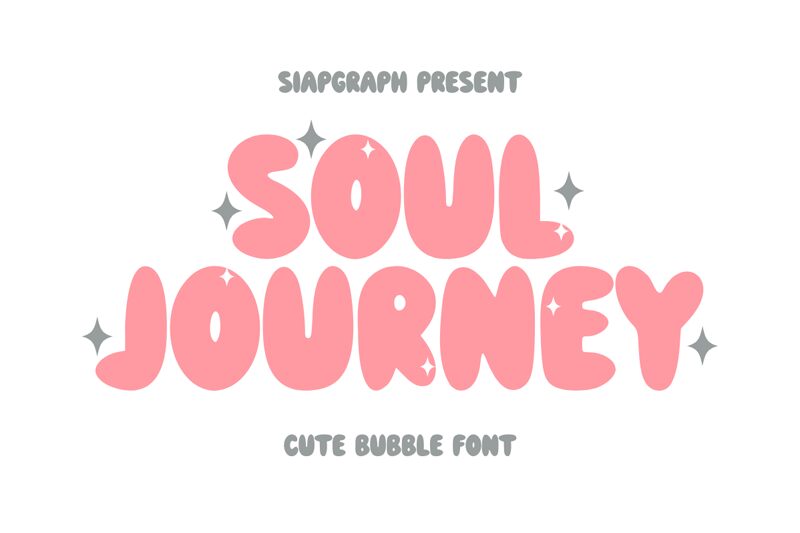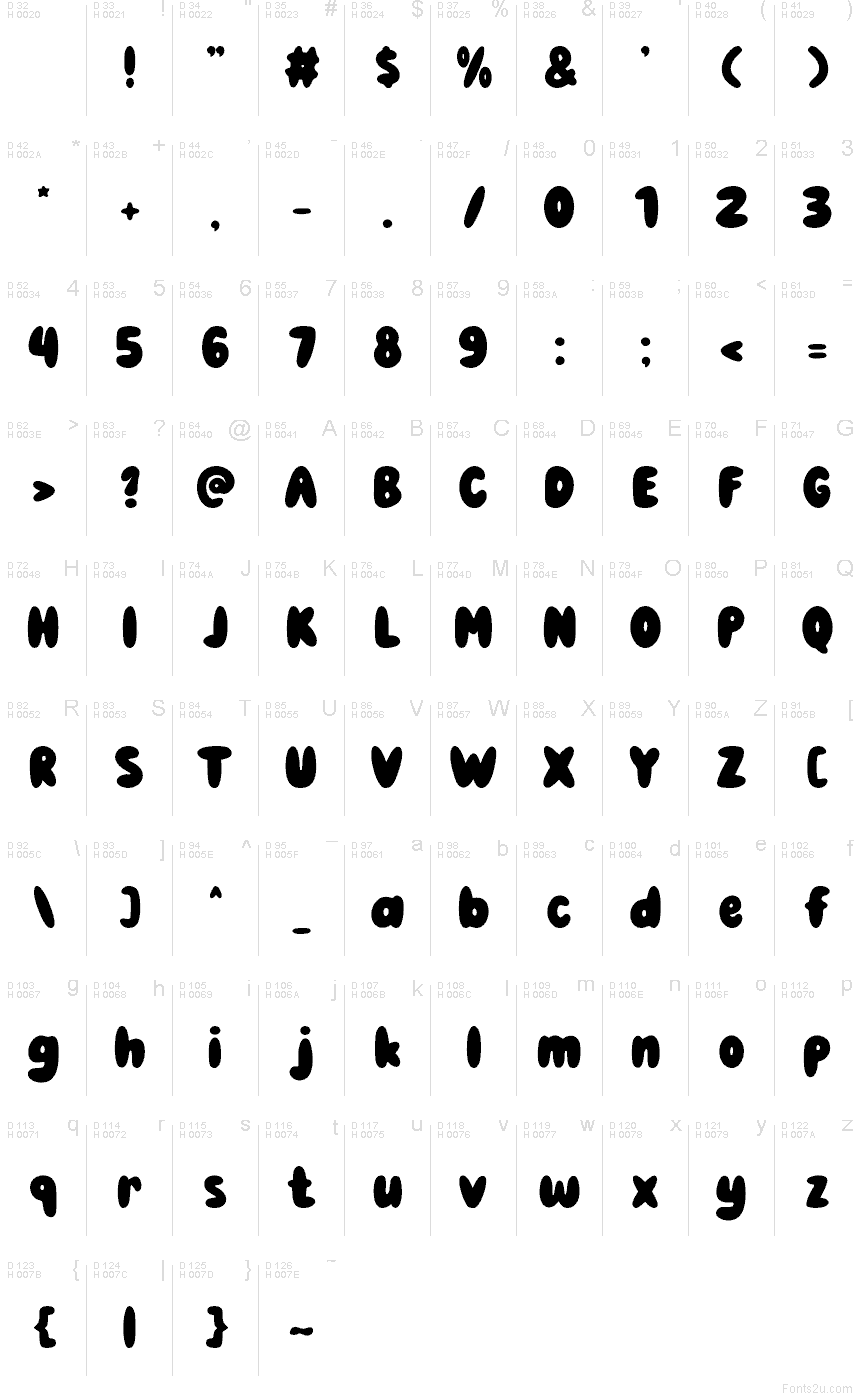
Soul Journey
Soul Journey je bezplatné kreslené display písmo s vypuklými, tekutými tvarmi, vďaka ktorým každé písmeno pôsobí, akoby bolo skôr odliate než nakreslené. Striedanie širokých zaoblených plôch a vysokých zvislých ťahov dodáva textu mäkký, pružný rytmus, ktorý sa odlišuje od klasických komiksových písiem.
Skvele sa hodí na narodeninové pozvánky, detské párty nápisy, obaly na sladkosti, návrhy nálepiek aj hravé náhľady na YouTube. Vďaka asymetrickým krivkám a hustému čiernemu prevedeniu je Soul Journey ideálne pre krátke nadpisy alebo logotypy, kde potrebujete priateľský a organický tvar, ktorý zaujme viac než bežné bublinové písmo.